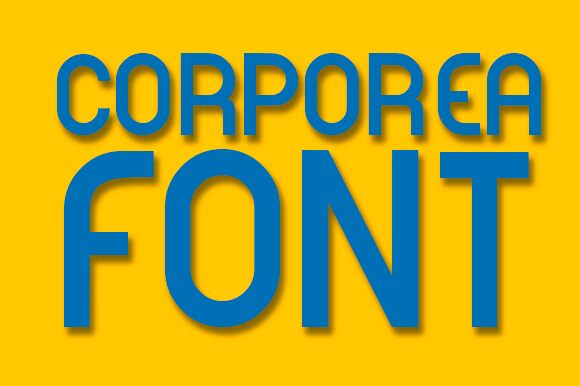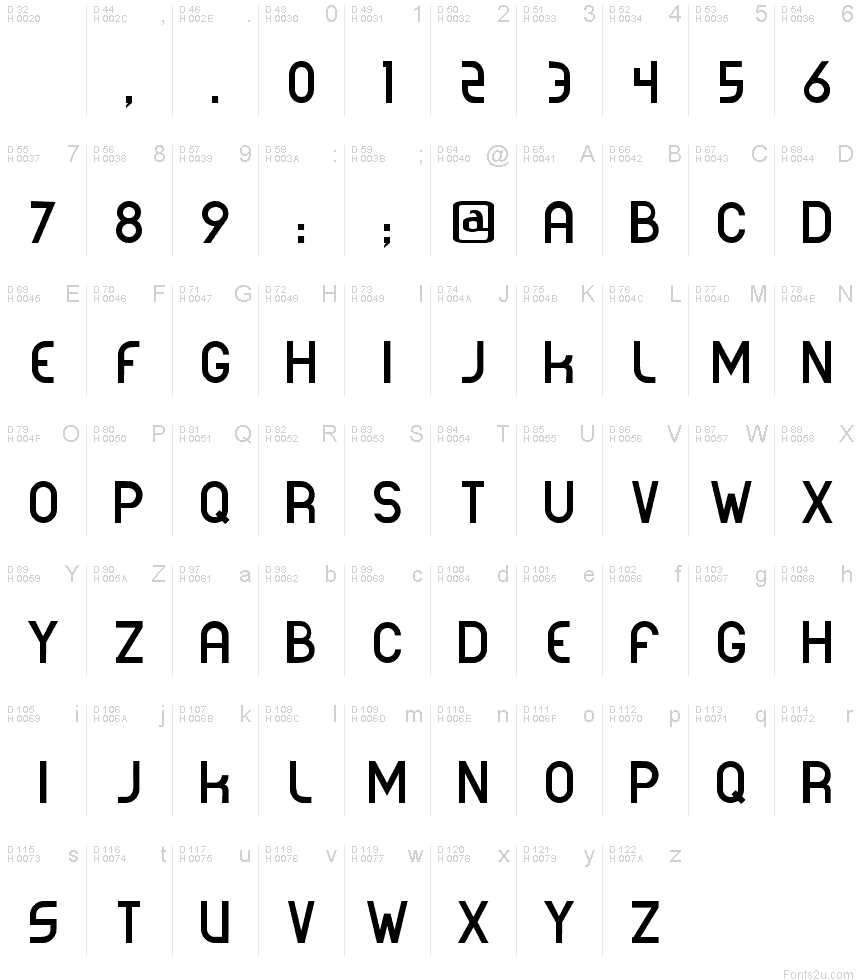
Font Corporea autorstwa Raula Pereza Canseco z Grafito Design to darmowy, geometryczny krój bezszeryfowy o odważnym, rurkowym charakterze. Litery przypominają gładkie metalowe rurki wygięte w wyraźne, modularne kształty – szerokie łuki, kwadratowe zakończenia i równy rytm nadają mu solidną, inżynieryjną obecność. Stała grubość linii sprawia, że wszystko pozostaje czyste i czytelne, a zaokrąglone światła liter dodają mu przyjaznej, niemal architektonicznej miękkości.
Stosując Corporea, zyskujesz wyrazisty głos w brandingu technologicznym, projektowaniu opakowań, systemach informacji wizualnej, plakatach eventowych i śmiałych logotypach. Ten darmowy font najlepiej prezentuje się w dużym rozmiarze, pozwalając zaokrąglonym prostokątom "oddychać", szczególnie w przestronnych nagłówkach i oznakowaniach. Świetnie łączy się z prostym krojem groteskowym lub humanistycznym sans w tekście głównym, pozwalając Corporea grać rolę przyciągającego wzrok bohatera.